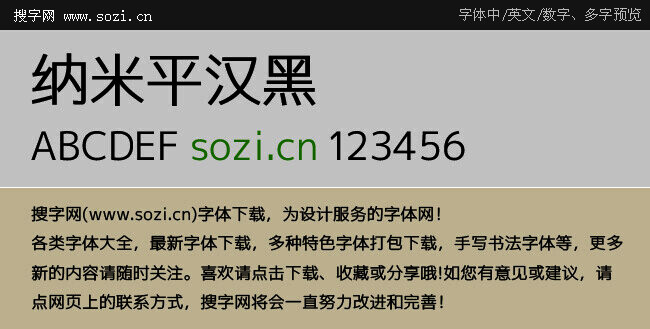
纳米平汉黑
搜字网提供一款纳米平汉黑中文艺术字体下载,纳米平汉黑是一款基于M+字体和EmpoSans制作的黑体补充项目,现已支持常用简体和繁体,将一些M+的字改为G源,再进行简体补充,且修复了EmpoSans的大多数bug(例如:字形粗细不一)。 这款字体无论是个人还是企业都可以自由免费商用,无需知会或者标明原作者。适合包装设计、海报设计、广告设计等应用。